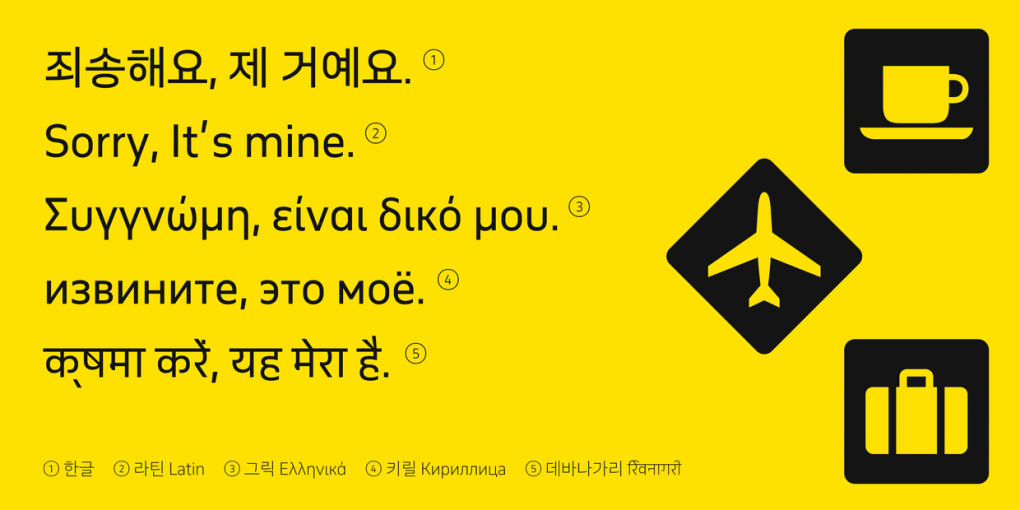
산돌 X 티포텍의 3번째 협업으로 탄생! 거대 폰트 패밀리를 가진 「SD 노벰버」를 소개합니다.
산돌 X 티포텍의 3번째 협업으로 탄생한, 거대 폰트 패밀리를 가진 「SD 노벰버」를 소개합니다.
「노벰버」는 한글, 라틴과 라틴 확장, 그릭과 그릭 확장, 키릴과 키릴 확장, 그리고 산돌 최초로 데바나가리 문자를 포함하여 270곳 이상의 언어권을 지원합니다. 또한 이탤릭과 산돌 최초의 배리어블 폰트까지 포함하여 총 20종으로 출시되는 그야말로 강력한 사용성을 지닌 폰트 패밀리이죠. 한 마디로, 도저히 수식어를 하나로 꼽을 수 없을 만큼 자랑하고 싶은 점이 많은 폰트라고 할 수 있겠네요.
멋진 결과물은 보이지 않는 노력이 만들어 내는 법! 자랑하고 싶은 점이 많은 폰트인 만큼,
SD 노벰버」 출시를 위한 여정은 길고 길었습니다.
티포텍과의 새로운 협업, 「SD 노벰버」
다국어 프로젝트를 다루는 일
하지만, 이러한 어려움을 해결하는 것이 바로 숙련된 폰트 디자이너들의 실력!💙